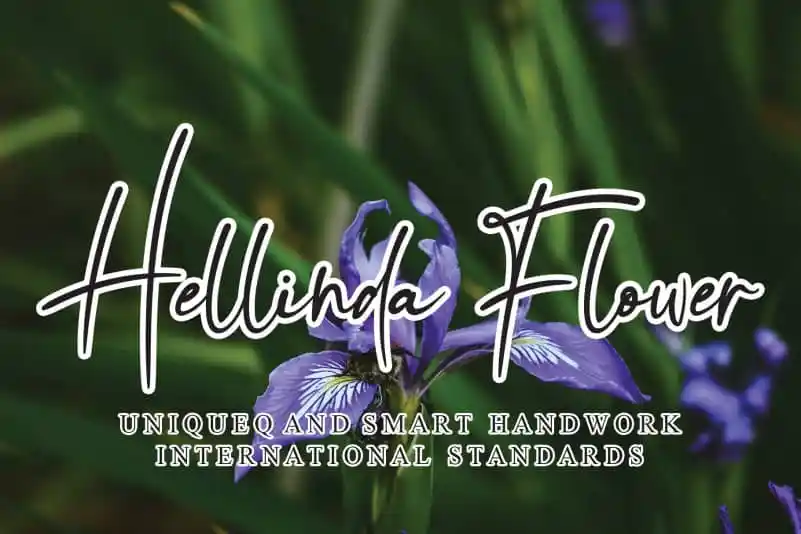
Hellinda Flower Handwritten Font – Download Grátis
A Hellinda Flower Handwritten Font é uma elegante e descontraída fonte escrita à mão que se destaca para quem deseja adicionar um toque especial às suas criações visuais. Ideal para logos memoráveis, identidades de marca impactantes e citações inspiradoras, esta fonte oferece cada letra com sua personalidade única e encantadora. Cada sílaba tem um brilho distintivo que torna seu design mais vibrante e atraente. Seja você um designer de marcas, uma agência de marketing ou simplesmente alguém que aprecia criar arte, Hellinda Flower é uma escolha perfeita para complementar qualquer projeto visual. Sua textura encantadora e personalidade única certamente farão sua obra mais especial.